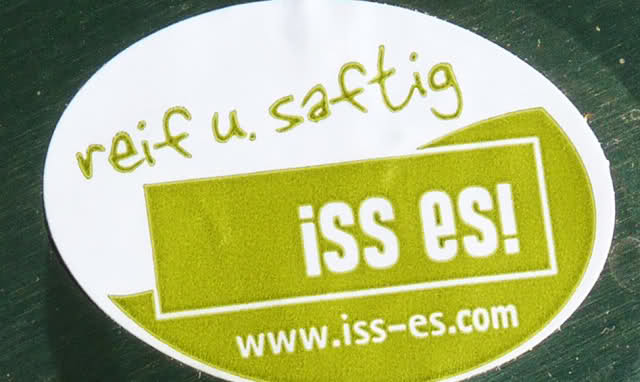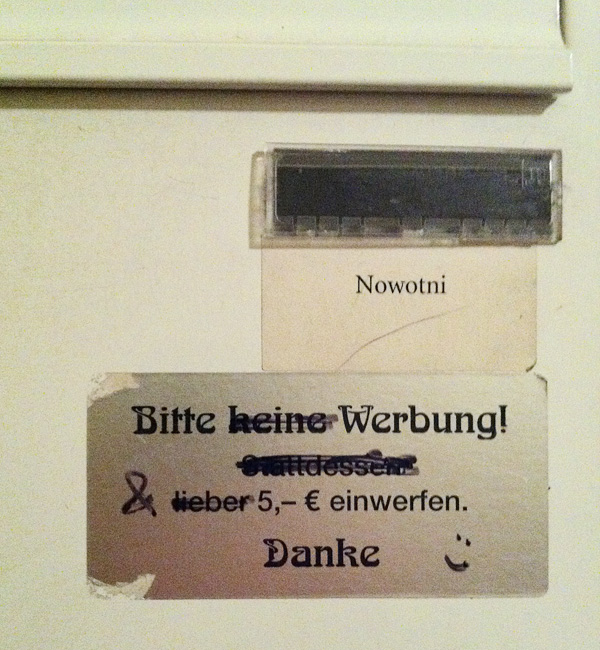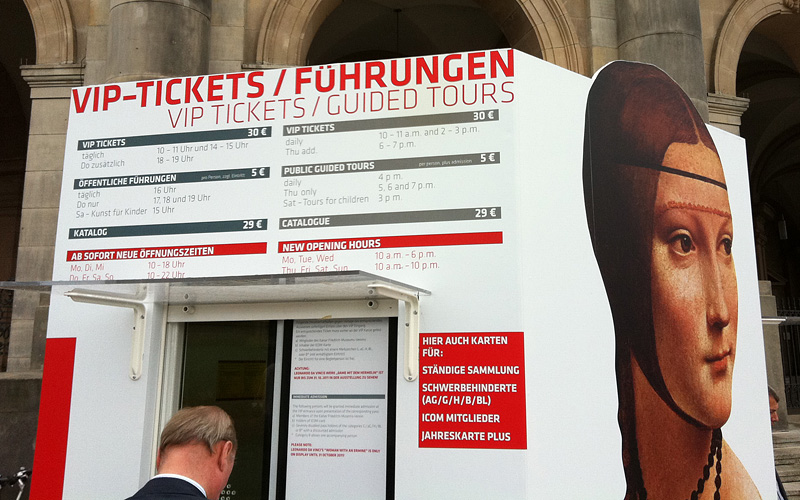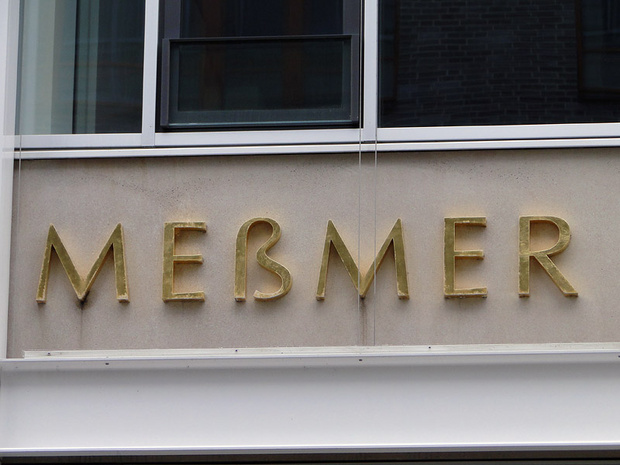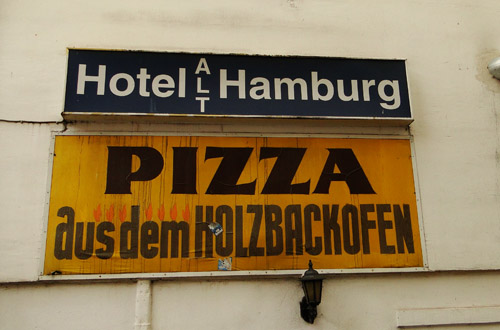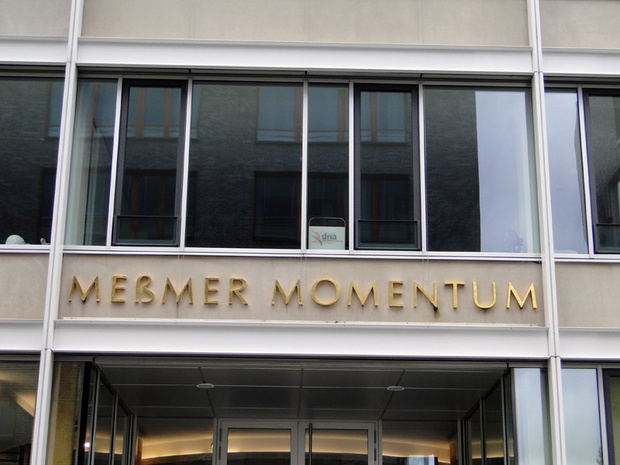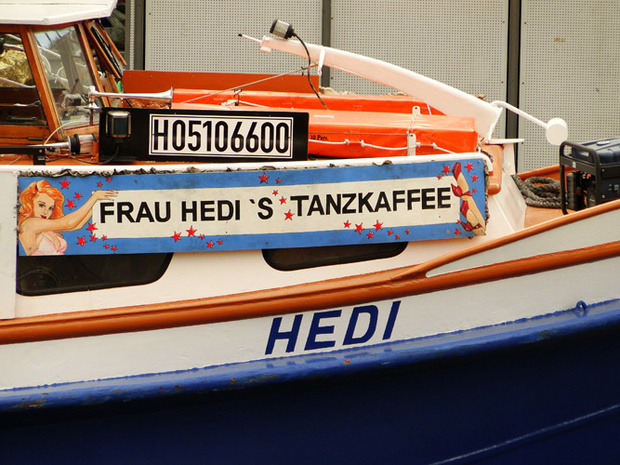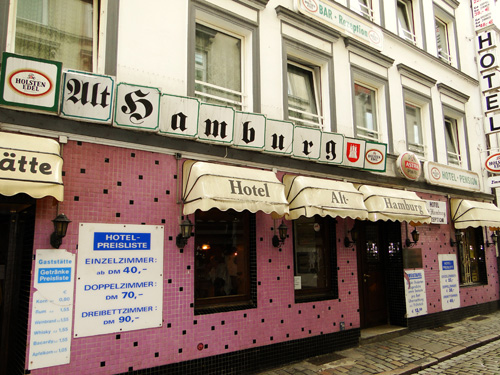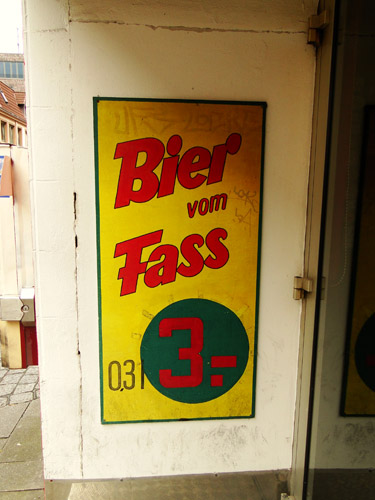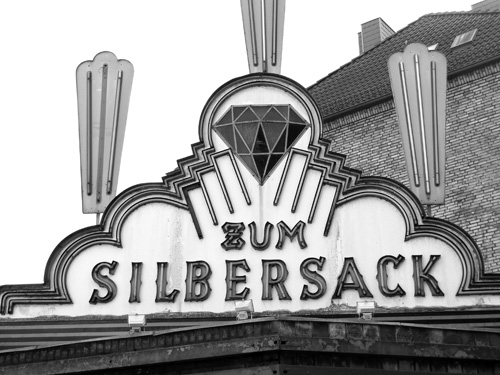
… Fühlt sich jemand angesprochen? :mrgreen:
Mit ihm zu kuscheln?
Neeee, lass mal lieber :shock:
An der Anzeige ist was faul:
Das ist keine Kuschel-Comic Sans :lol:
An der Anzeige ist was faul:
Das ist keine Kuschel-Comic Sans :lol:
Dafür auf deren Webseite!
Ansonsten schließe ich mich bertel an ... lass mal lieber ...
Aber das Thema gehört eigentlich in die Gender-Diskussions-Abteilung (Trainer und TrainerInnen) ...
Recht hast Du. Außerdem – meine Güte! So weit ist es schon gekommen, dass die Leute einen Trainer zum Kuscheln brauchen … :-o:neenee:8-)
Wieviel war denn die richtige Antwort wert?
Kuscheltrainer ist schon klasse, wa?
Dringendst gesucht ...! Das wusste ich noch nicht.
Aber Trainer und TrainerInnen - da frag ich mich doch, wer damit alles gemeint ist?!
Ja, das ist echt …
…!
Damit verbringst Du also Deine Freizeit … ;-)
Ergänzende Frage: Mit dem Gestalten oder dem Ausfüllen dieser Heftchen?
Gestaltet hat das wohl ein 100-Jähriger mit Bildern aus den 80er Jahren. :-|
Man kann jedenfalls mit Fug und Recht vermuten, dass die Macher des Rätselheftes keine typophile Zielgruppe anpeilen … :-D
... Es sei denn sie sind cool krass fette Schiffeversenker (Hosetiefträger war gestern)
Witzig, ja – aber wirklich gut :-?
Ich glaube ein großes, kräftiges ! hätte viel mehr Ausdruckskraft. Man setzt es ja nicht grundlos, um es dann in der Zeile zu verstecken ...
Es war wohl mehr die Geometrie, die den Gestalter gereizt hat. Ich find es gut :-)
Großes Kino? In Hamburg?? Warte mal … :kram räum rümpel:
Da habe ich doch auch noch was:
:nana: Keine Scherze mit dieser altehrwürdigen Hamburger Institution! Da ist doch nur das Leerzeichen etwas knapp ausgefallen … der DA™ schmerzt mich schon mehr, wenngleich es sich auch um ein sehr altes und ehrwürdiges Exemplar handelt. ;-)
Also Schnitzel, dass Du jetzt schon so offensive Werbung für Dich betreibst … tse! ;-) Habe ich gerade im Internet gefunden: